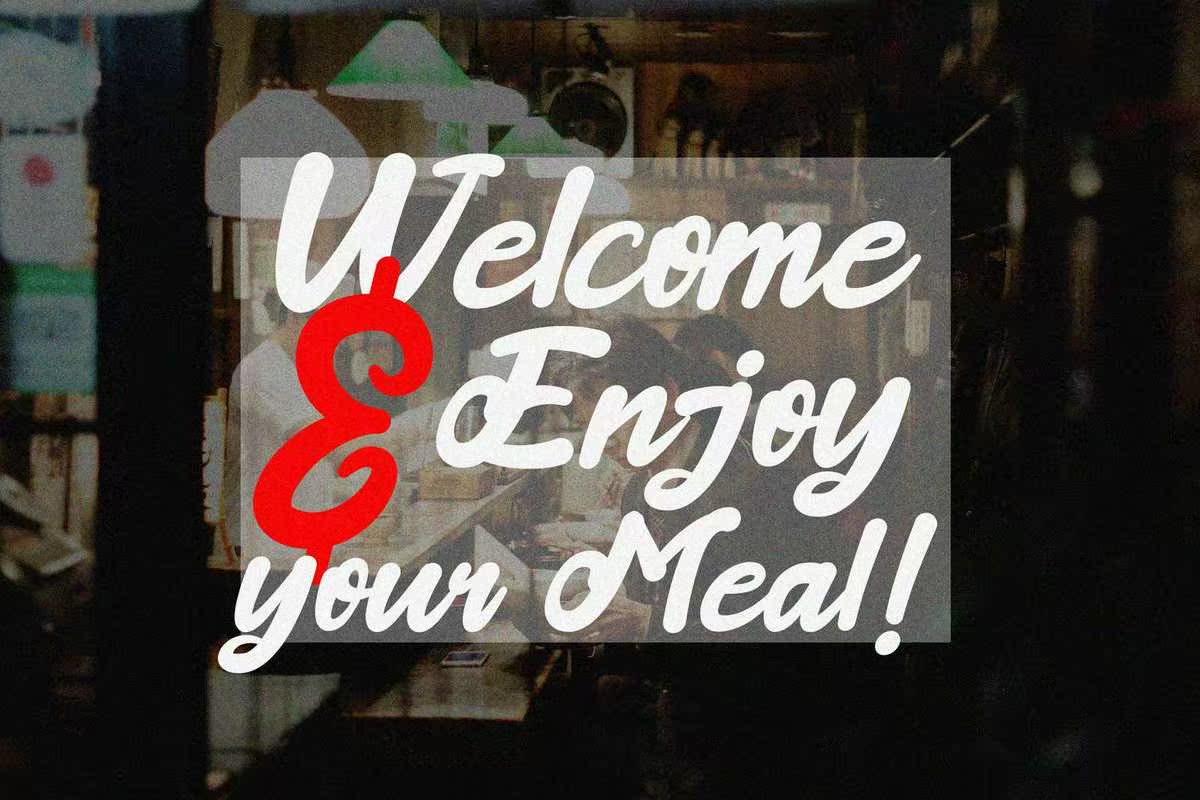
Santonyis Anastonishing and Boldbold Handwriten字体,精心制作,使您的头条线和徽标项目成为一种时尚风格。这种字体具有强烈、自信和活力,可以为您的设计增添怀旧的色彩。Santonyis Anastonishing and Boldbold Handwriten字体,精心制作,使您的头条线和徽标项目成为一种时尚风格。这种字体具有强烈、自信和活力,而动感又能为您的设计增添怀旧的色彩。